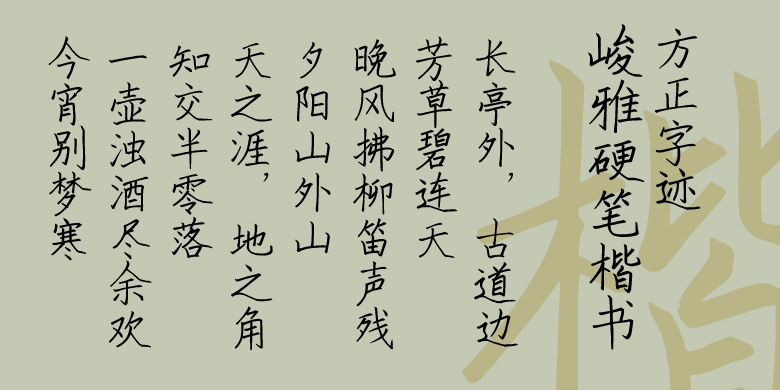
方正字迹-峻雅硬笔楷书
安景臣
常规书写·硬笔
该字体是采用硬笔风格书写的楷书字体。鉴于目前硬笔字库繁多,但好的楷书字体、尤其是能用于字帖出版的字体比较少的现状,设计书写了此套字体。该字体采用硬笔风格书写,安景臣本人书写,使字库风格得到了完美统一,实用性与艺术性兼备。该字库可用于字帖出版、影视字幕、商品包装、商标标志、广告语宣传、网络宣传等场景。